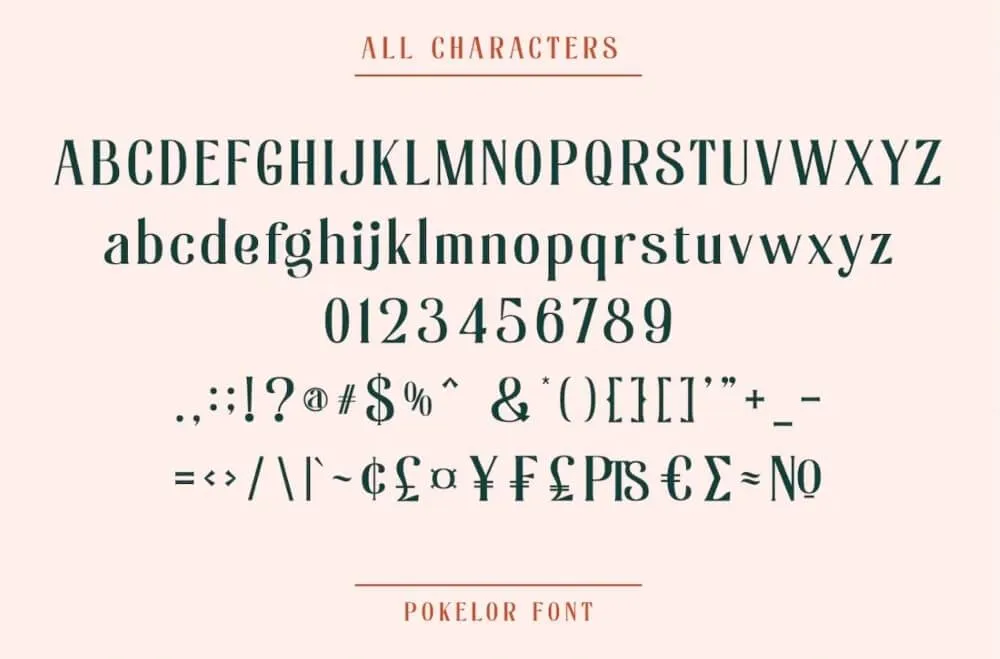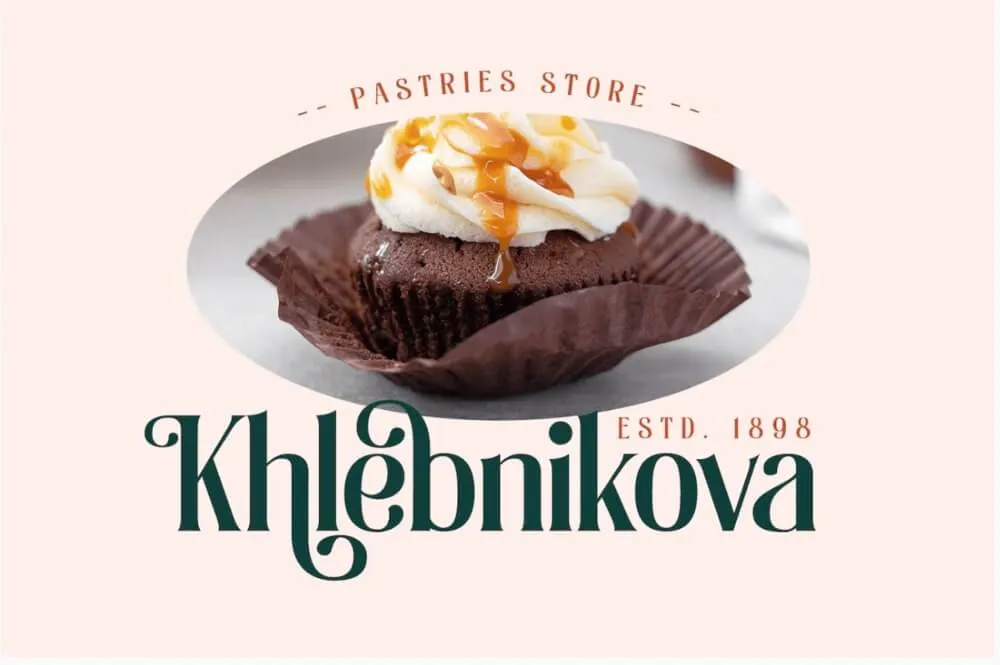
Font Pokelor là một phông chữ display serif được thiết kế đẹp mắt với sự hài hòa giữa chức năng và vẻ đẹp cho bạn ấn tượng thanh lịch, hiện đại nhưng không kém phần trang trọng. Các yếu tố liên tục của các móc nhỏ giúp mắt nhìn liên tục từ chữ cái này sang chữ cái khác.
Với khoảng cách rộng và các chữ cái dễ nhận thấy, phông chữ này thực sự dễ đọc mà bạn có thể áp dụng cho mọi kích thước văn bản. Hơn nữa, hãy tận hưởng những tính năng thú vị có sẵn trong phông chữ này.
Đặc trưng font:
• Bộ phong cách
• Hỗ trợ đa ngôn ngữ
• PUA được mã hóa
• Chữ số và dấu câu
Pokelor phù hợp nhất cho các dự án thiết kế khác nhau, chẳng hạn như áp phích, biểu ngữ, logo, bìa tạp chí, trích dẫn, tiêu đề, sản phẩm in, thư mời, thẻ tên, hàng hóa, mạng xã hội, v.v. Tìm hiểu thêm các cách sử dụng phông chữ này bằng cách xem qua tại phần xem trước phông chữ.